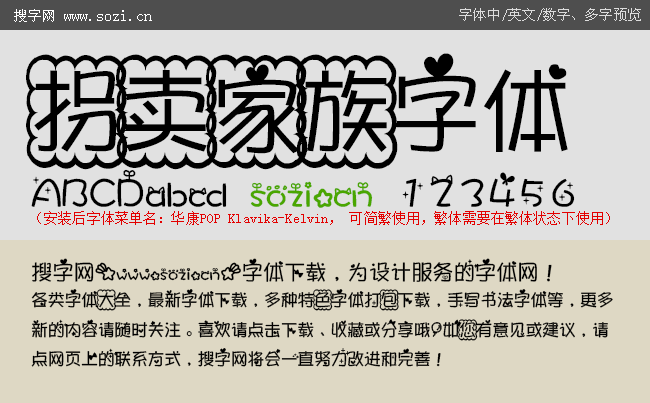
拐賣家族字體
搜字網(wǎng)給大家提供一款很有趣的手機(jī)中文字體下載。拐賣家族字體,這款手機(jī)字體是在華康POP字體筆畫間插入了卡通花紋和可愛的花邊。趣味性實(shí)足,該手機(jī)字體個(gè)性實(shí)足,趣味性強(qiáng),又保持了文字的識(shí)別度,特別適合喜歡手機(jī)字體個(gè)性一些的朋友在手機(jī)上安裝使用。